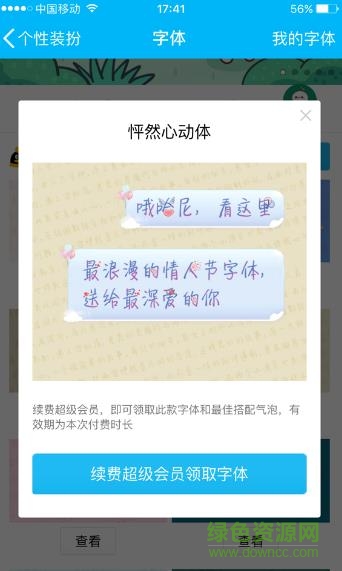
怦然心動體ttf字體在qq字體中受到了廣大用戶的喜愛,在交流談話的過程中將帶給你極致的視覺體驗,同時讓你能夠在手機上安裝這款字體,每天使用這款字體閱讀小說,發(fā)送消息,進行文字編輯,十分不錯哦!
qq怦然心動字體小編點評
這款字體的最大特色在于讓你輔一看到它就能夠?qū)λ鼉A心不已,是一款擁有精美視覺效果的字體樣式,同時不僅局限于在手機,qq使用還能夠運用到媒體制作當中!
qq怦然心動字體
qq怦然心動體字體ttf字體介紹